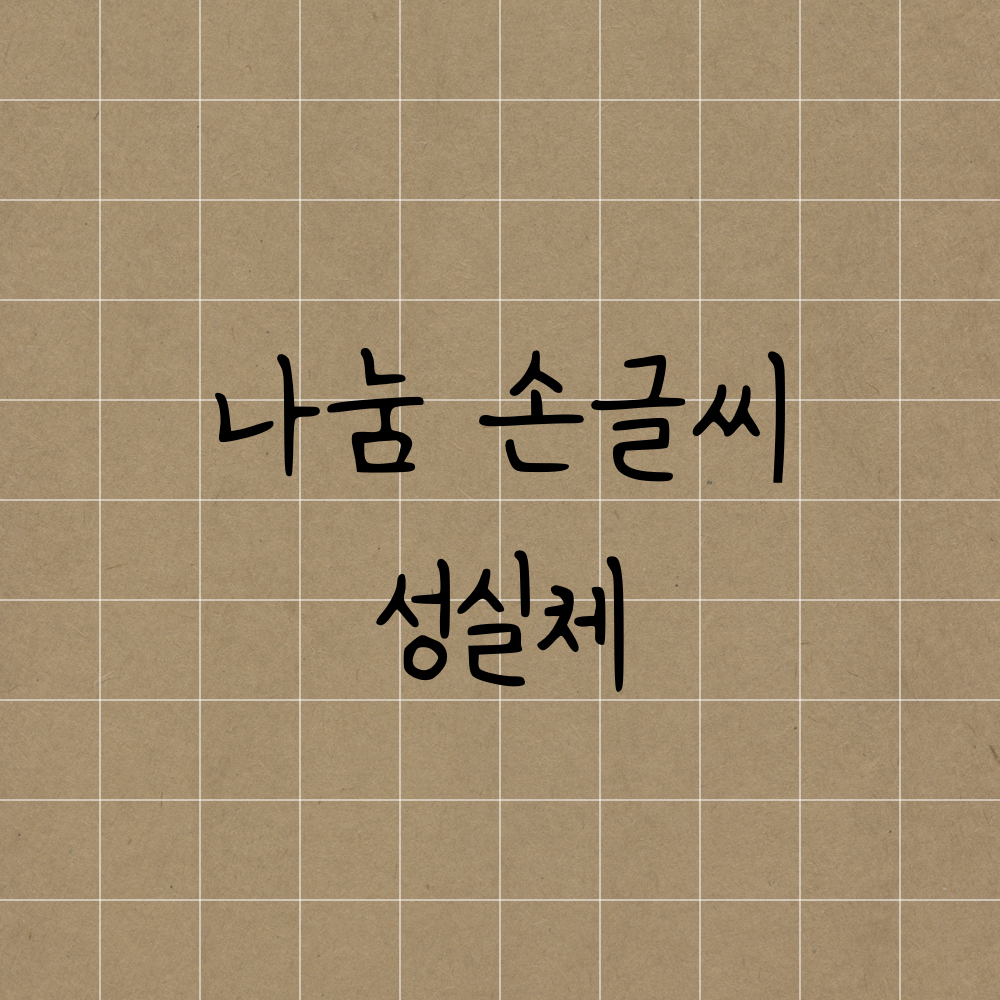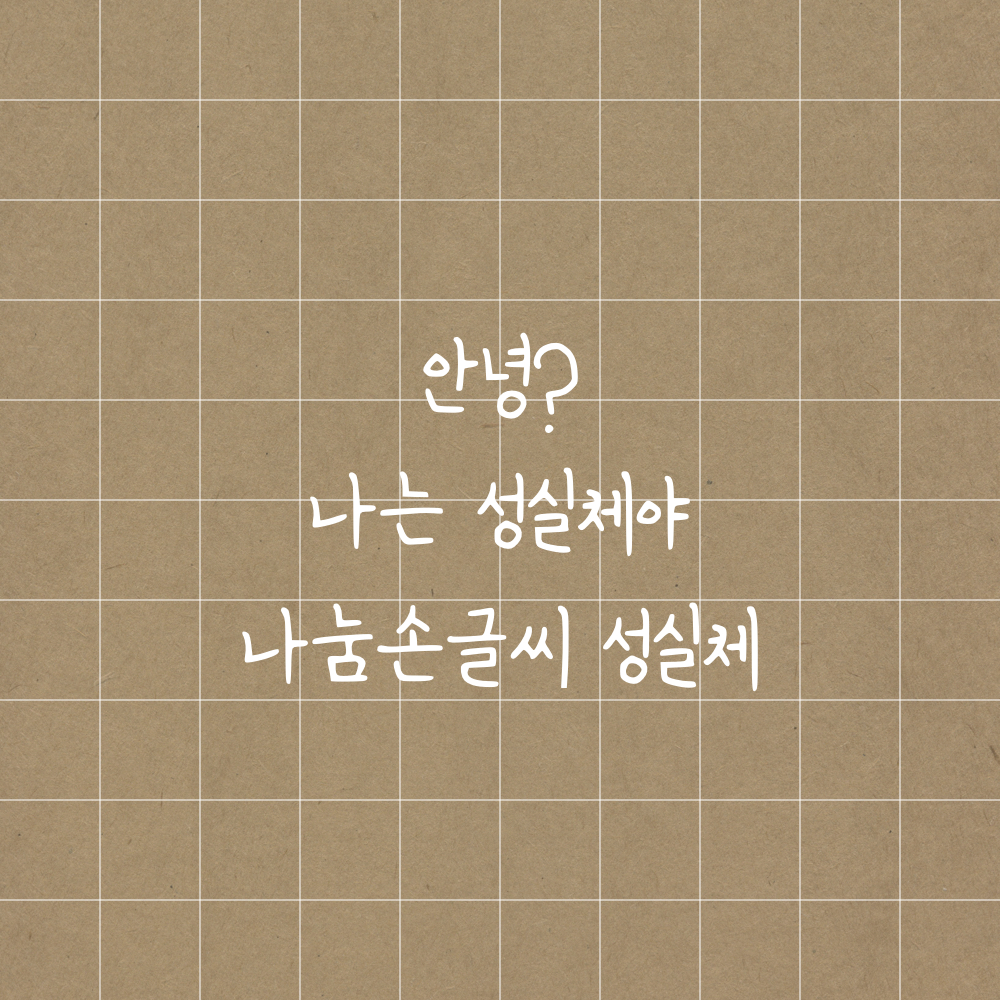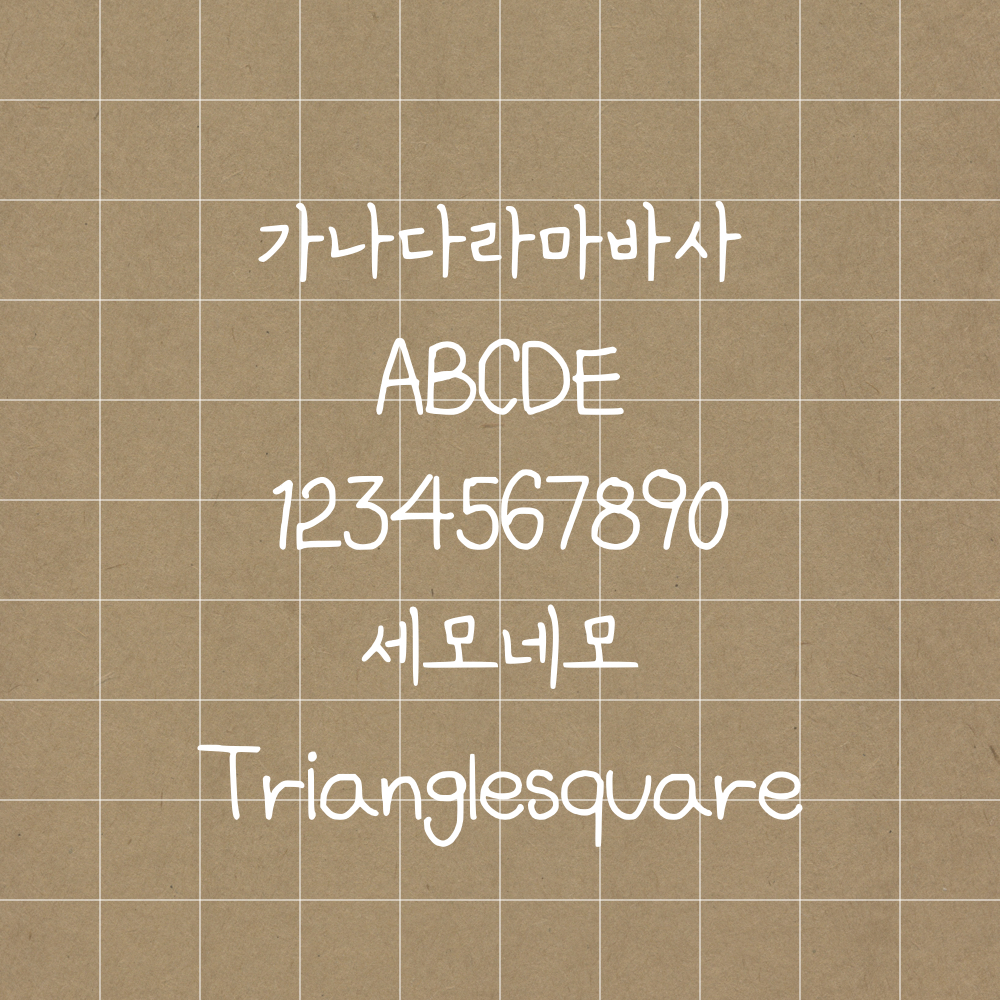
오늘의 폰트는 성실체입니다💛 꾹꾹 눌러쓴 글씨체가 매력적인 폰트😆
독서 기록장 폰트에 사용하고 있는 성실체의 매력을 알아봅시다.
더도 말고 덜도 말고 내 스타일이다...💕
독서 기록장에 폰트로 쓰는 이유, 전체적으로 진하다🤓
한국어와 숫자 글씨 크기가 크고 예쁘다..💜
너무 유명해지지 않았으면 하는 마음..📖 나만 알거야~~!!!